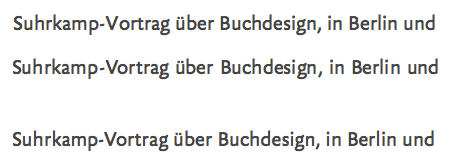
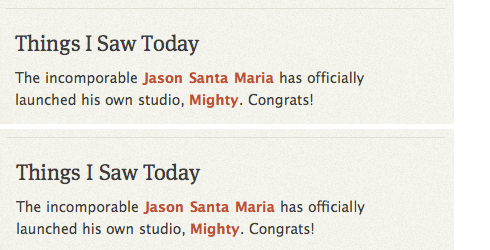
Gestern stieß ich auf die Internet-Testseite Cross-browser kerning-pairs & ligatures, deren Überschrift sich übersetzen lässt mit »browserübergreifendes Kerning plus Ligaturen«. Dort heißt es, dass schon einige Browser die metrischen Daten von Fonts unterstützen, zum Beispiel Firefox, Safari 5 und Chrome. Einzige Voraussetzung: die Option optimizeLegibility muss eingeschaltet sein, was nur bei Firefox von Hause aus der Fall ist (für Textgrößen über 20 Pixel).
Ich habe es eben ausprobiert und bin teils begeistert, teils unschlüssig. Mann muss schon eine mit Webfonts gebaute Internet-Seite besuchen, um die Verbesserung der Lesbarkeit zu erleben … denn die Standard-Schriften Verdana, Arial, Georgia und Co enthalten größtenteils weder Kerning, noch Ligaturen.
Den oben gezeigte Vergleich habe ich auf simplebits.com erzeugt, indem ich die Safari-Erweiterung ein- und ausgeschaltet habe (geht wunderbar in Echtzeit mit geöffnetem Voreinstallungsfenster). Weitere Webseiten, auf denen man die Verbesserung der Lesbarkeit gut nachvollziehen kann sind:
So richtig toll ist das Ergebnis bei Webfonts manchmal jedoch nicht. Zum Test das Plugin mal aktivieren und sich dann die Überschrift des Suhrkamp-Posts auf dem Fontblog anschauen. Vor allem auf “Buchdesign” achten.
Das stimmt, Sven. Darum habe ich auch geschrieben: »… ich bin teils begeistert, teils unschlüssig.« In der obigen Abbildung habe ich das von Dir beschrieben Phänomen dargestellt. Ganz oben: Safari ohne Kerning, darunter Safari mit Kerning und ganz unten Firefox – die beste Darstellung. Meine Vermutung geht dahin, dass Typekit sein Safari-Rendering nachjustieren muss: Die Pixelsprünge und das Kerning zusammen liefern Löcher und Buchstabenberührungen. Firefox dagegen greift auf den selbst gehosteten Webfont zu (im Fall von Fontblog FF Yoga Sans), und das Ergebnis sieht ziemlich gut aus.
Bei mir zerhaut es mit optimizeLegibility in Safari die Umbrüche. Da werden plötzlich Zeilen länger als Sie eigentlich dürfen, und brechen in die nächste Spalte ein :/ (Firefox scheint auch ohne diese Zeile Ligaturen zu benutzen)